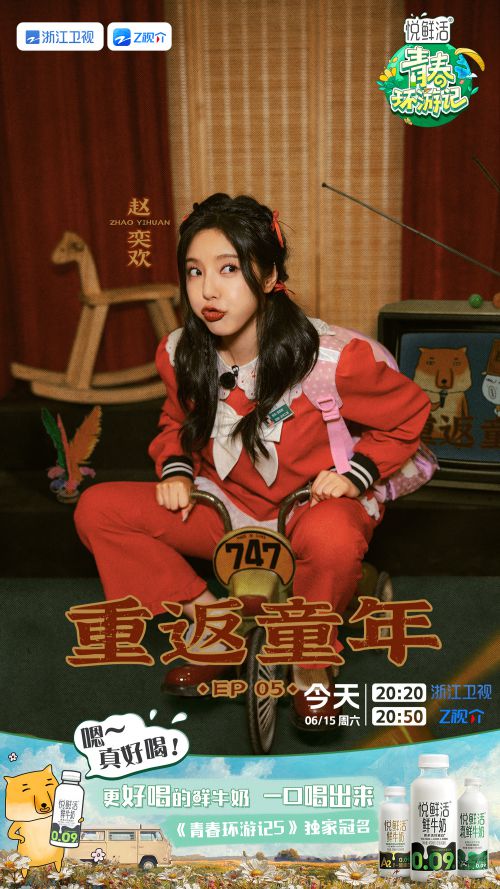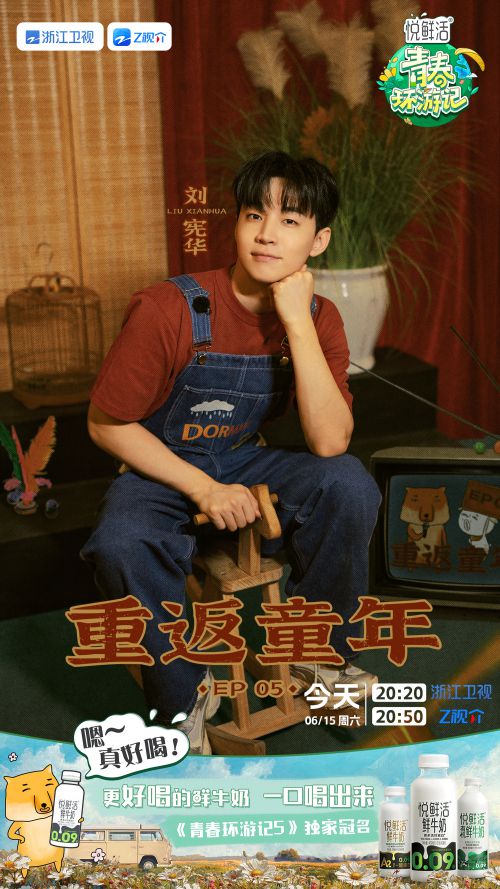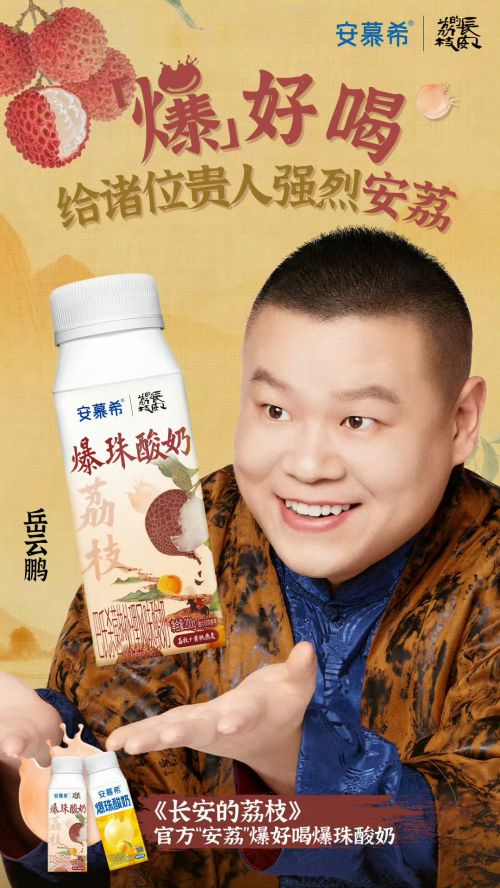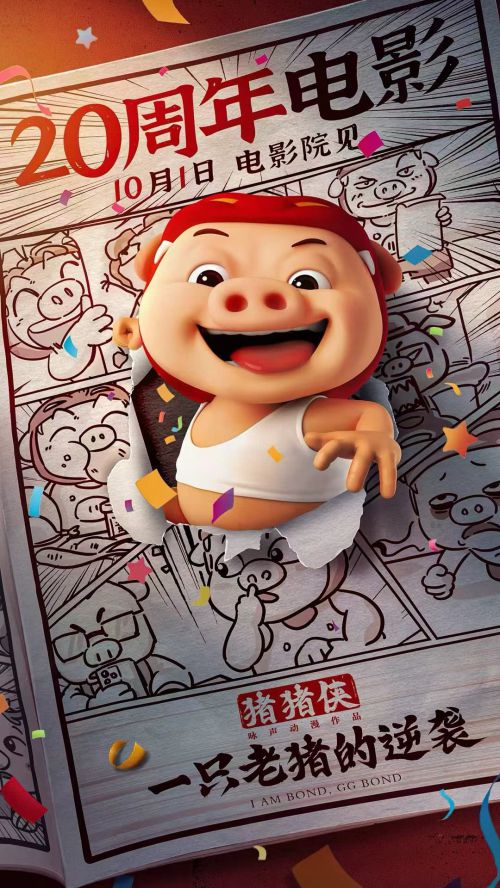
江西拙楷
字库品牌: 黄煜臣
江西拙楷是一款充满古韵的中国风楷体字体,犹如古籍中的墨宝重现。字体采用方正稳健的字形结构,重心居中且中宫松紧适度,展现出楷书特有的端庄气质。其方头笔画搭配均匀的线条粗细,融入传统书法的装饰性笔触,既保留楷书的端庄大气,又通过断开的笔画设计增添古朴拙趣。 江西拙楷由设计师黄煜臣精心打造,旨在传承传统书法美学,同时兼顾数字时代的阅读体验。作为免费商用字体,它为设计师提供了兼具艺术性与实用性的创作选择,适用于标题设计、古籍排版、文化海报、传统节日宣传等多种场景。 江西拙楷将古典美学与现代设计需求巧妙融合,让每一个文字都散发着沉静典雅的东方韵味。